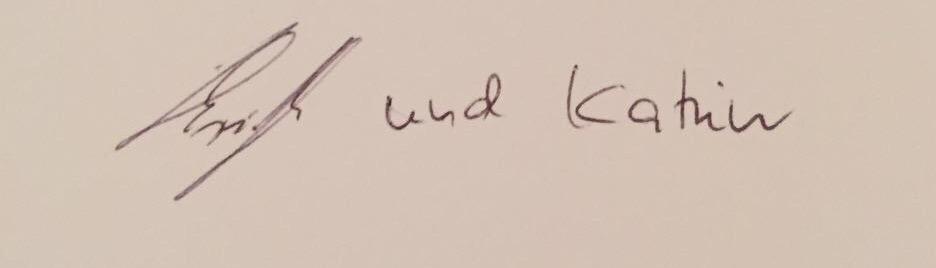
[Mitglied Luke…] Geschrieben August 30, 2017 Teilen Geschrieben August 30, 2017 Hallo, ich bin neu hier und hoffe das ich richtig bin. Wir haben zu unserer Hochzeit eine Glückwunschkarte bekommen und können den "ersten" Namen nicht Endziffern. Wir würden gerne wissen von wem die Karte ist. anbei das Bild. Vielen vielen Dank! Link zu diesem Kommentar
[Mitglied Diet…] Geschrieben August 30, 2017 Teilen Geschrieben August 30, 2017 Könnte das Erich sein? Link zu diesem Kommentar
[Mitglied Luke…] Geschrieben August 30, 2017 Themen-Ersteller Teilen Geschrieben August 30, 2017 Hallo Dieter, danke für deine schnelle Antwort. Wir dachten auch kurz an Erich, allerdings kennen wir kein Erich ... :-/ es müsste was anderes heißen... Link zu diesem Kommentar
[Mitglied 0ebf…] Geschrieben August 30, 2017 Teilen Geschrieben August 30, 2017 Glückwunsch zur Hochzeit Könnte mit M anfangen … Link zu diesem Kommentar
[Mitglied catf…] Geschrieben August 30, 2017 Teilen Geschrieben August 30, 2017 Ernst? Oder Katrin fragen? Link zu diesem Kommentar
[Mitglied Þors…] Geschrieben August 30, 2017 Teilen Geschrieben August 30, 2017 Also ich lese auch nur Erich. Ich vermute einfach mal, dass Katrin einen Neuen hat. Link zu diesem Kommentar
[Mitglied Henn…] Geschrieben August 30, 2017 Teilen Geschrieben August 30, 2017 Zwei Threads in einem... Der Partner von Katrin könnte vielleicht Friedrich heißen. Link zu diesem Kommentar
[Mitglied Chri…] Geschrieben August 31, 2017 Teilen Geschrieben August 31, 2017 Der zweite Buchstabe ist für mich ein h. Der letzte auch. Die Unterlänge könnte auf ein ph hindeuten. Und die Schmiererei auf einen relativ langen Namen. Christoph? 1 1 Link zu diesem Kommentar